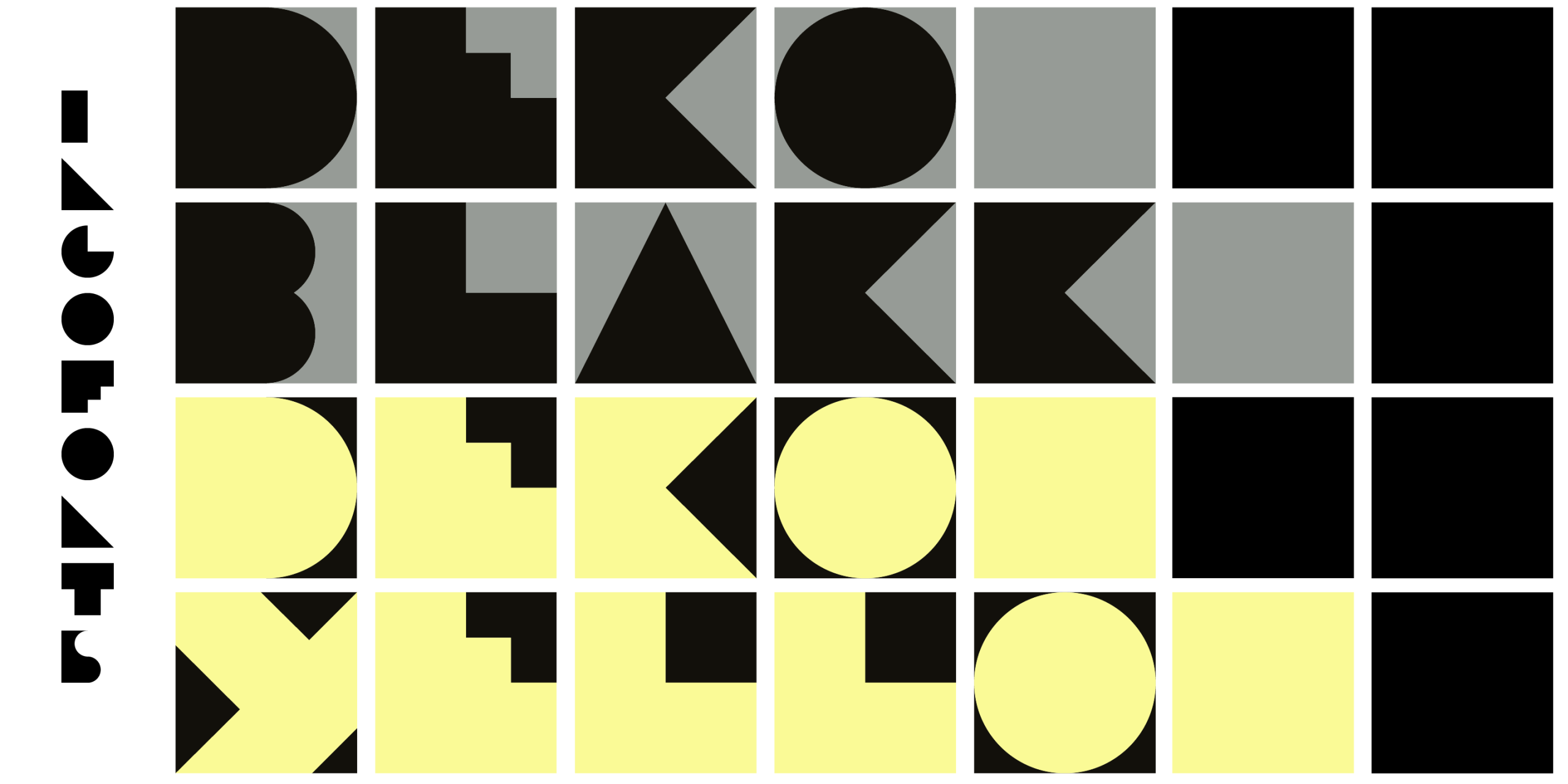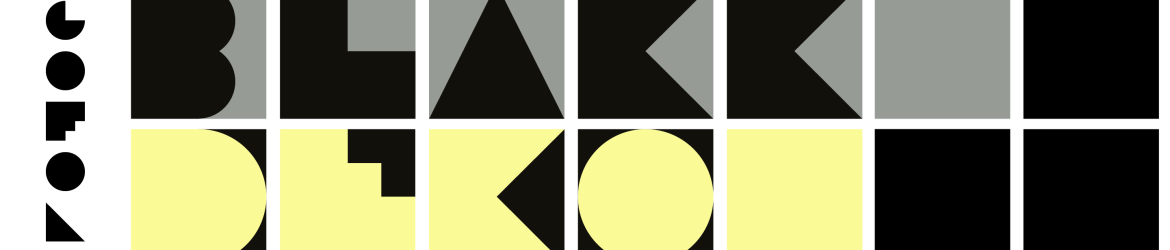
Introduzimos uma nova opção no vasto leque das fontes de exibição, Dékó Font, que é absolutamente gratuita. Desenhada por Ingo Zimmerman e publicada pela ingoFonts, esta fonte tem um carácter único dentro da categoria de tipos de mão-desa. Dékó não se assemelha a uma fonte convencional. É mais como um artefato decorativo, mas ao mesmo tempo funcional e minimalista. Suas formas geométricas são arranjadas em quadrados que resultam numa pequena obra-prima gráfica. As letras permanecem tipicamente reconhecíveis, mas de uma maneira tão modificada que cada uma parece ser um pequeno logotipo à sua própria direção. Este tipo é perfeito para aquelas aplicações que exigem uma aparência única e imediatamente agradável ao olho. É ideal para o design gráfico, a criação de marca ou qualquer aplicação visual onde uma fonte semelhante não existe no mercado. O Dékó Font oferece um toque de excentricidade que não só torna a sua utilização um prazer, mas também faz com que aquele objeto ou texto se destaque na composição. Não importa qual seja o seu estilo ou aplicação, o Dékó font terá uma presença marcante e única. Semelhante a um artigo de arte em vez de apenas um tipo de escrita, ele será capaz de tornar qualquer projeto no qual esteja presente mais notável.